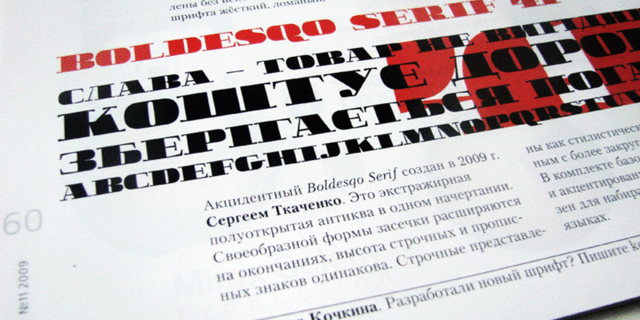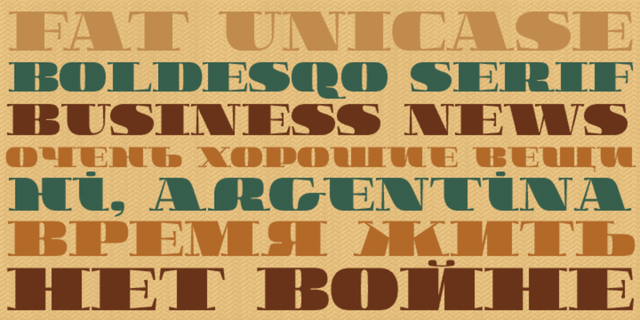
Шрифт Boldesqo Serif 4F
Жирный широковатый сериф для заголовков и плакатов. Разработан Сергеем Ткаченко в 2010 году.
Качества и характер:
убедительный, тяжелый, устойчивый, сильный, самобытный, пузатый, толстый, старомодный, оригинальный, характерный, дорогой, роскошный, экстравагантный, причудливый, вычурный, цыганский, заметный, броский, огромный, демонстративный, артистичный, выразительный, знойный, жаркий, твердый, красивый, богатый, старинный, претенциозный, эстетский, нонконформистский, экспериментальный, яркий, активный, пивной, тропический